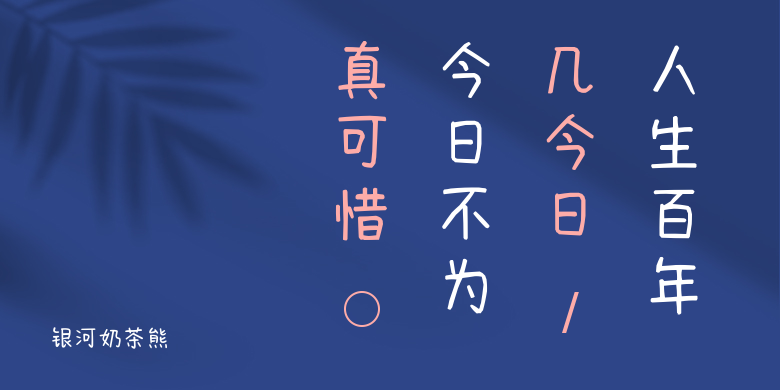
银河奶茶熊
银河奶茶熊,这款字体结构工整、笔画清晰,兼顾美观与易读性,适用于标题、正文、海报、包装、LOGO 等多种场景。字形优雅稳定,风格百搭耐看,适配日常排版与创意设计,让文字呈现更舒适、更具质感。银河奶茶熊一笔一画,皆是细节,以均衡的比例、流畅的线条打造舒适视觉体验,字形端正大气,风格简约现代。无论是商业设计、品牌宣传还是日常排版,都能轻松驾驭,让文字更有格调与力量。银河奶茶熊字体下载。